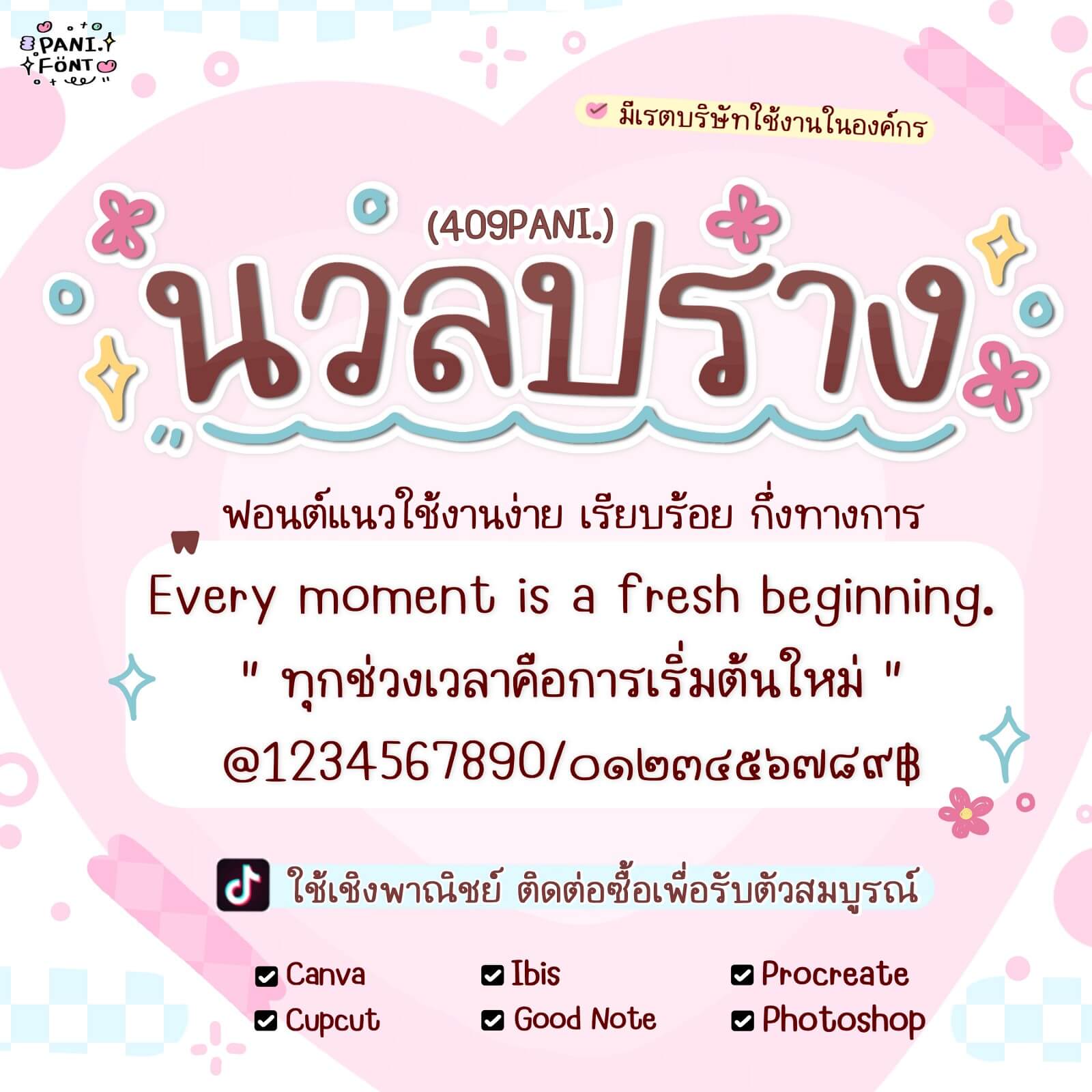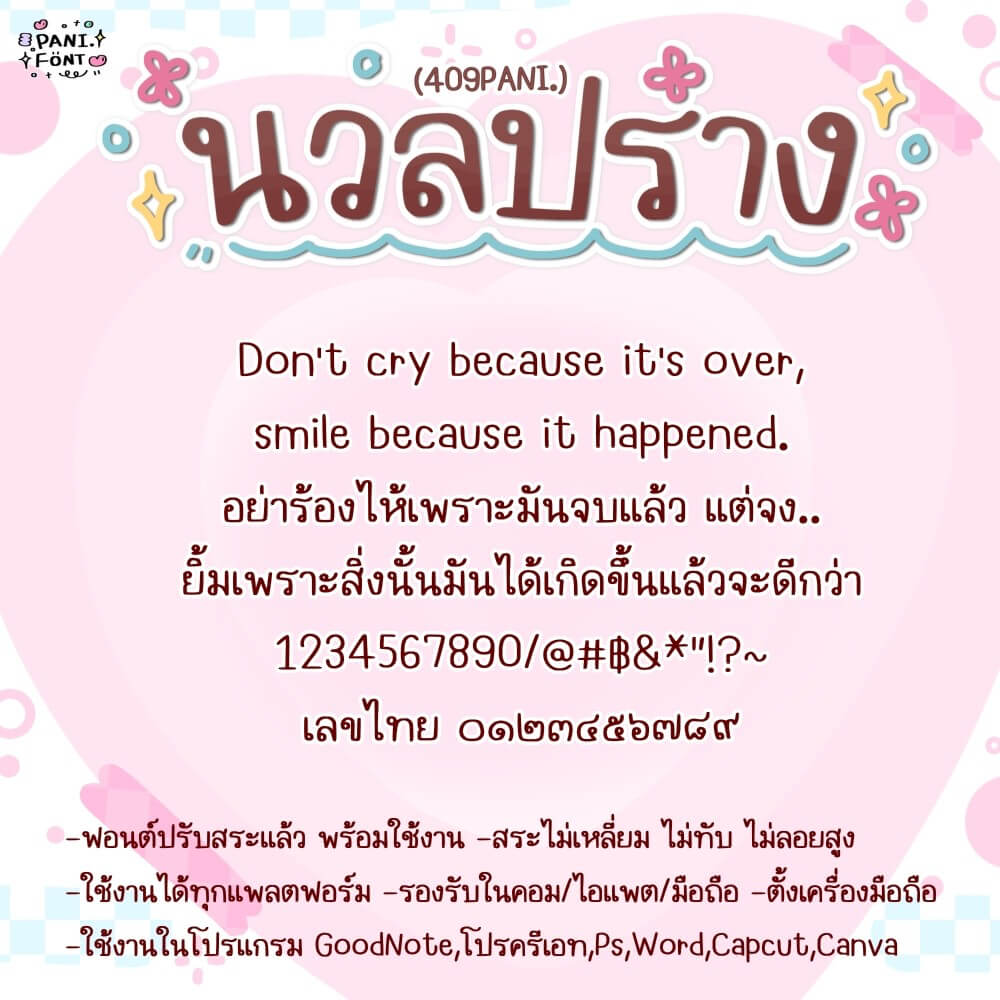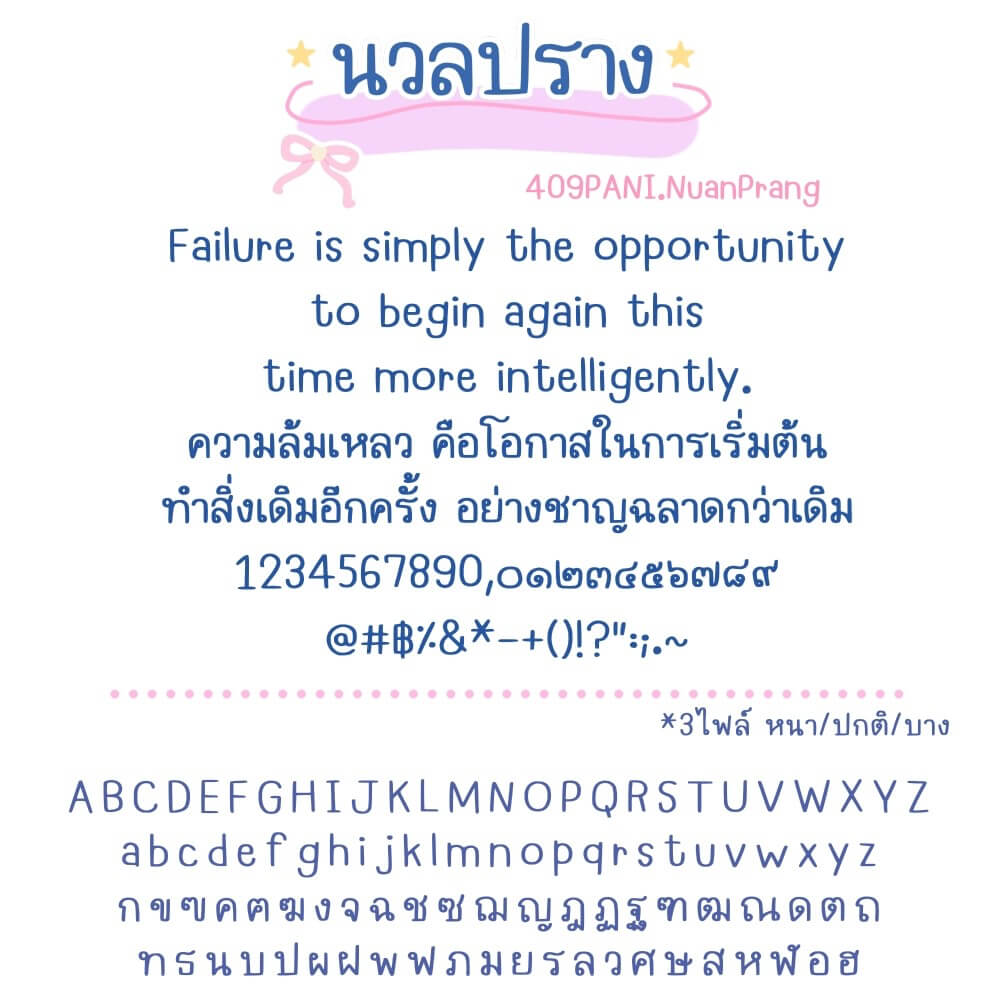
409PANI.นวลปราง
ฟอนต์ 409PANI.นวลปราง – ใครว่าฟอนต์เรียบร้อย จะน่ารักไม่ได้ สายตั้งเป็นฟอนต์เครื่อง ฟอนต์รายละเอียด หรือสายเรียบร้อยแบบกึ่งทางการ ต้องถูกใจสิ่งนี้